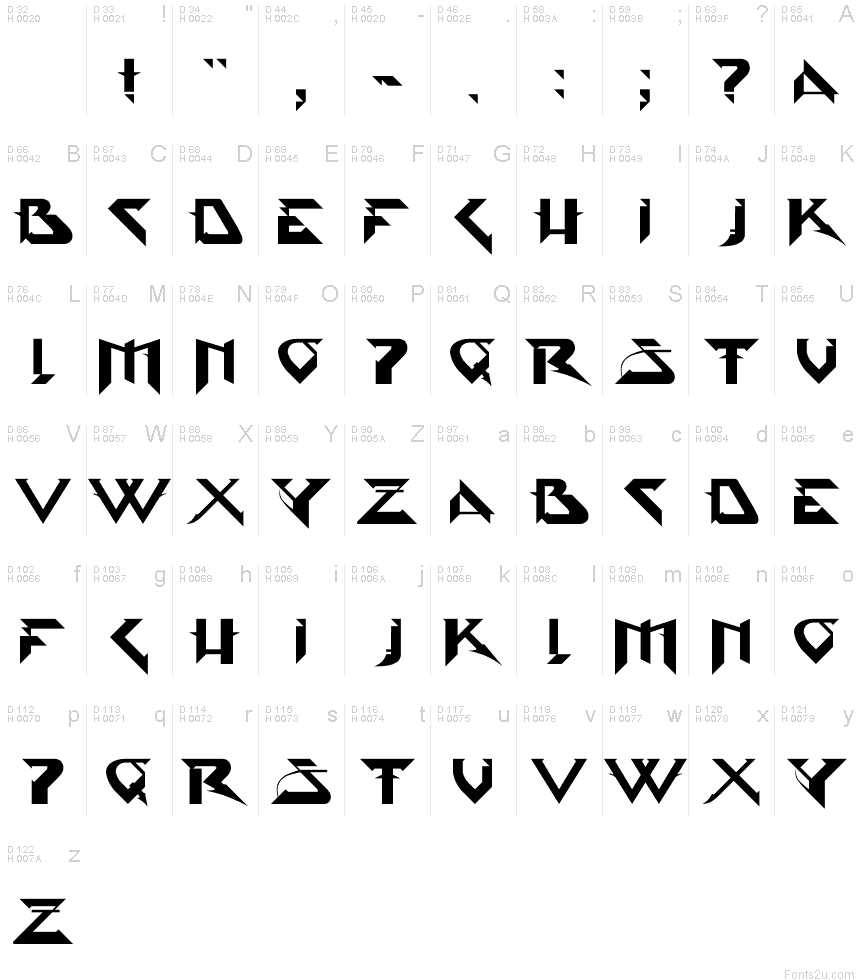
PsyType to nowoczesny, darmowy krój gotycki o futurystycznym, ostrym jak brzytwa charakterze blackletter. Litery łączą ciężkie, blokowe formy z długimi, ukośnymi cięciami i ostrymi połączeniami, dzięki czemu klasyczna gotycka estetyka zostaje odarta z ozdobników, stając się czymś chłodniejszym, bardziej surowym i lekko psychodelicznym.
Świetnie sprawdzi się na plakatach muzycznych, w brandingu streetwearowym, na okładkach albumów, planszach tytułowych i w krótkich nagłówkach, gdzie zaledwie kilka liter musi błyskawicznie nadać ton. Jako darmowy font, PsyType wyjątkowo dobrze sprawdza się w monogramach i zwartych logotypach, ponieważ twarde kąty i nagłe wcięcia nadają nawet bardzo krótkim napisom napiętą, niemal emblematyczną formę.